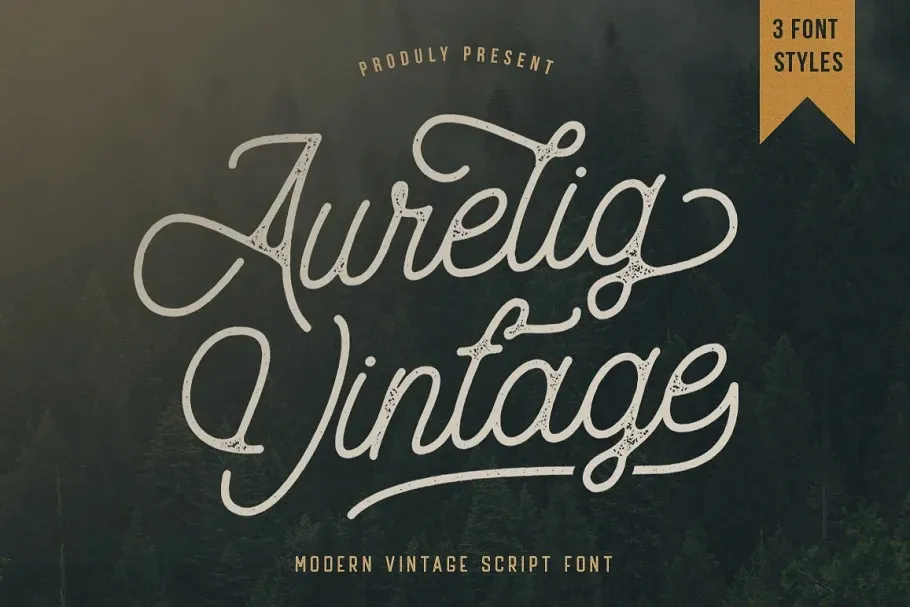
Aurelig Font Family – Download Grátis
A Aurelig Font Family é uma família de fontes script que traz a característica única de uma tipografia monolineada mas com uma textura mais irregular e natural. Esta fonte, criada pelo designer Vultype Co., apresenta uma forma bruta ao longo da linha principal do texto, oferecendo uma experiência visual distintiva àqueles buscando um toque de originalidade em suas criações digitais. Com sua textura marcante que contrasta com as linhas retas e precisas dos monoline fonts convencionais, a Aurelig se destaca como uma opção versátil para designers gráficos. Suas formas suaves e irregularidades naturais permitem um toque criativo e emotivo em designs digitais, trazendo vida à sua mensagem ou arte sem perder a essência da tipografia monolineada. Ideal tanto para aplicar em design editorial como em criações de arte digital, a Aurelig é uma escolha que promete criar uma impressão única em qualquer projeto visual.